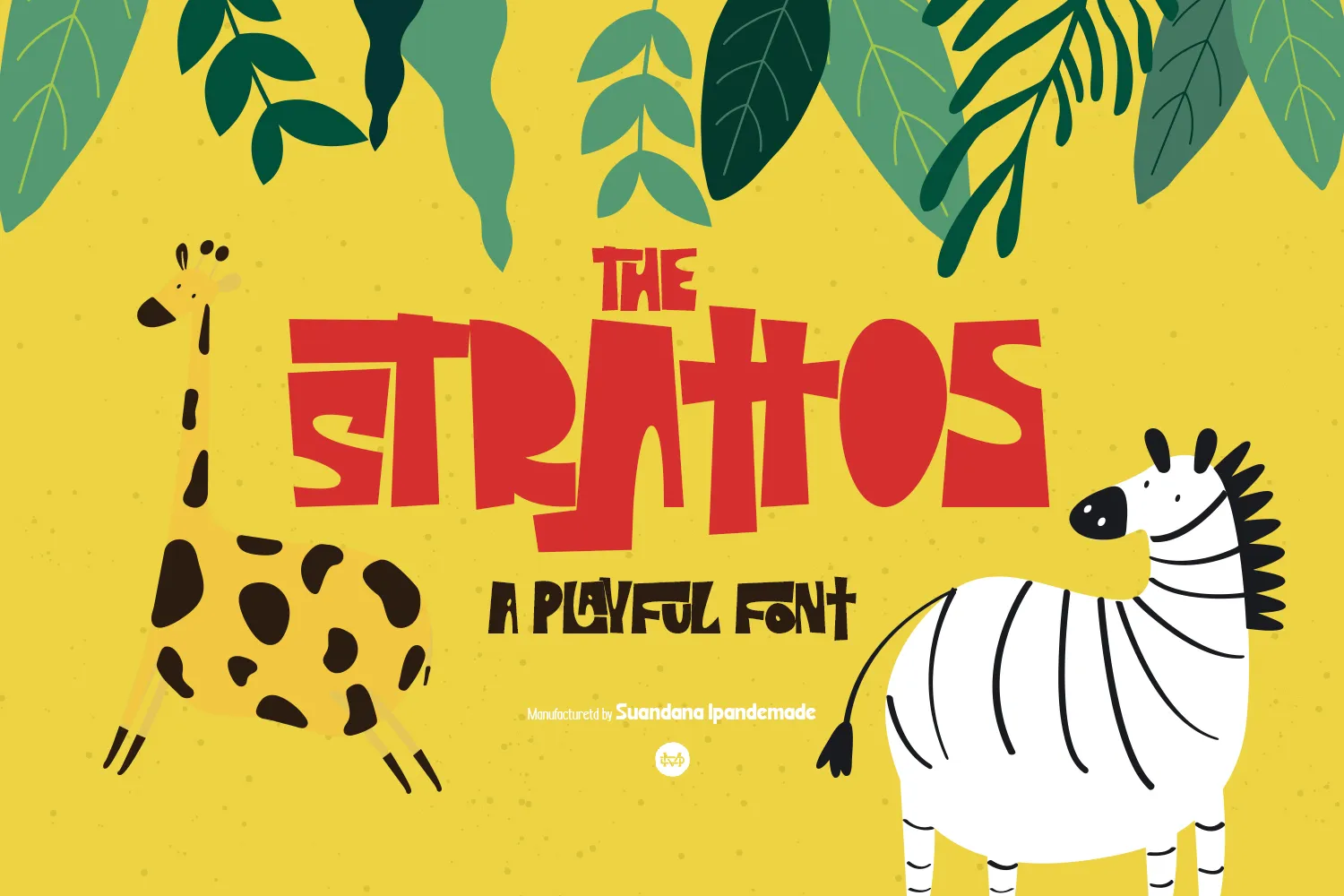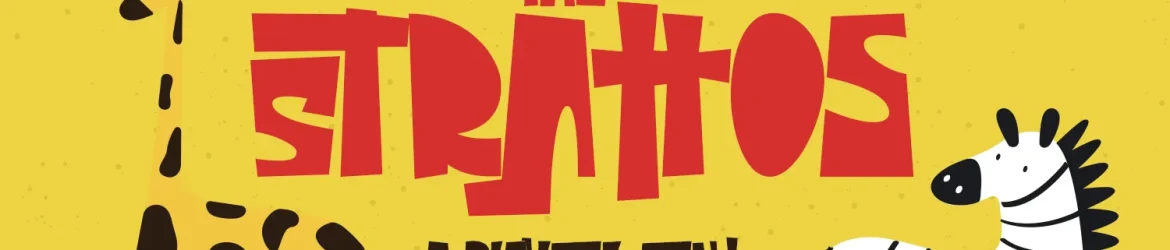
The Strattos Font – Download Grátis
A fonte ‘The Strattos Font’ foi criada para atender às necessidades dos profissionais de design que procuram uma fonte de exibição poderosa e enérgica. Ideal para uso em livros, rótulos, camisetas ou até mesmo como marca registrada de um produto. Suas linhas fortes e vibrantes tornam-a perfeita para destaque nos títulos dos produtos, embalagens e convites. Seja qual seja o projeto que você está trabalhando, ‘The Strattos Font’ estará sempre pronto para dar vida a seus projetos. Não importa se é uma etiqueta de um produto ou uma camiseta personalizada, essa fonte irá garantir que sua marca seja notada e destacada. Combinar design com força, ‘The Strattos Font’ está aqui para ajudá-lo a expressar sua identidade visual de maneira assertiva.